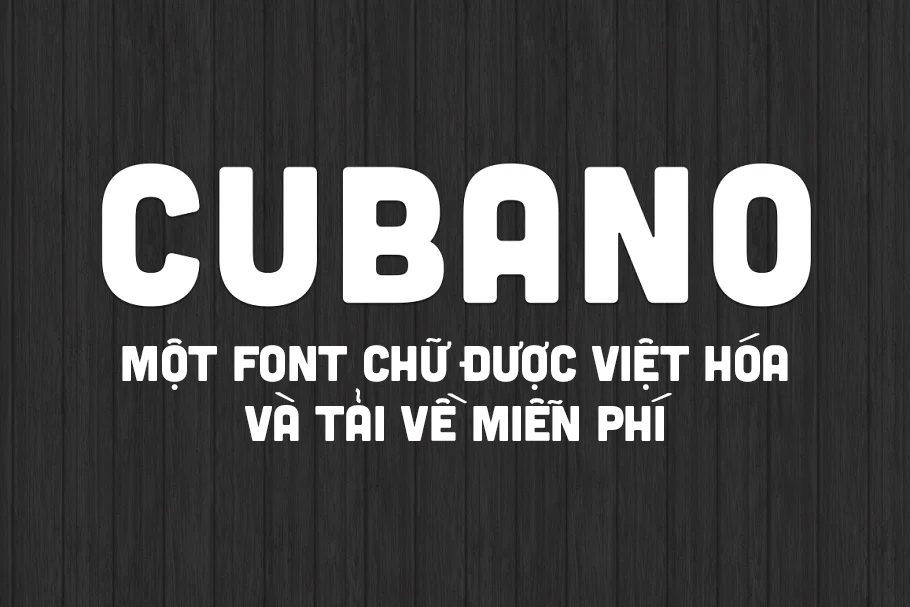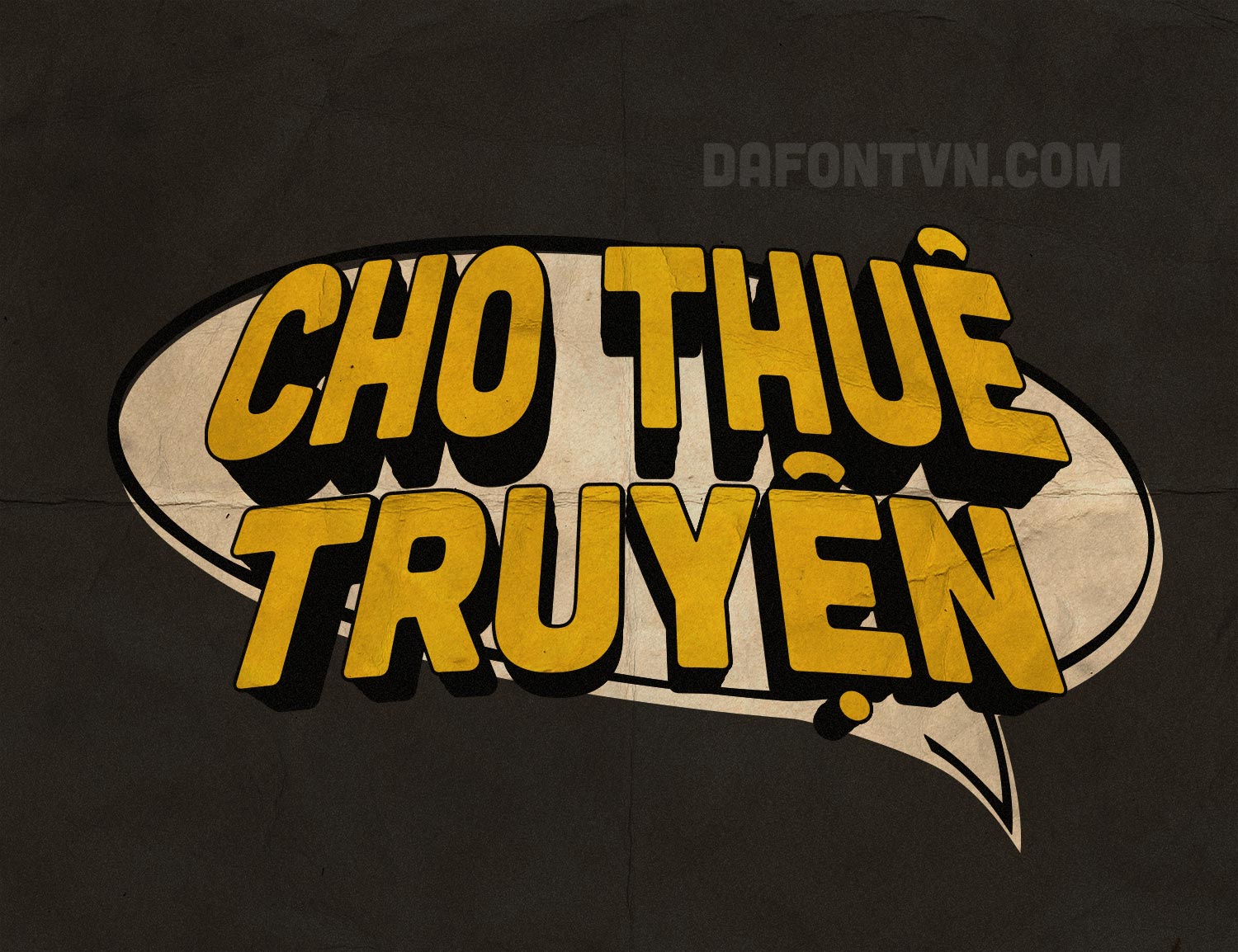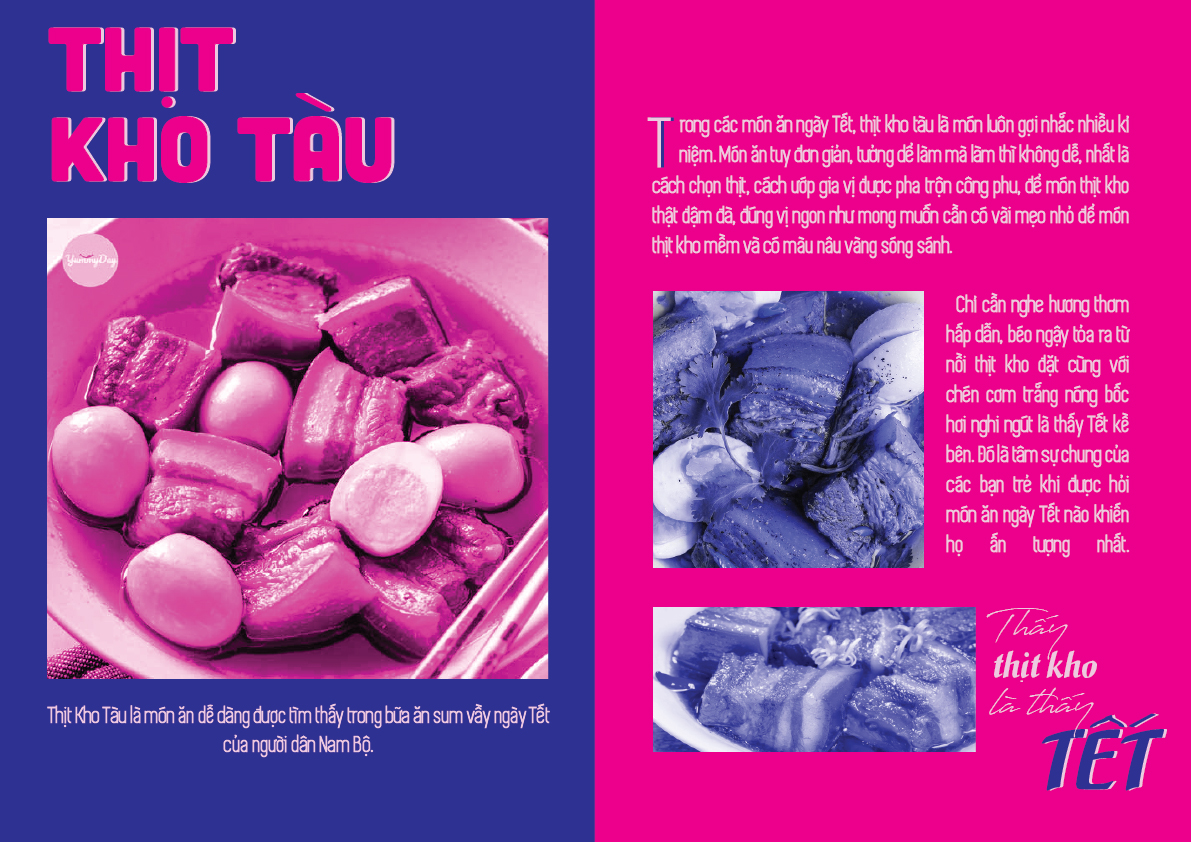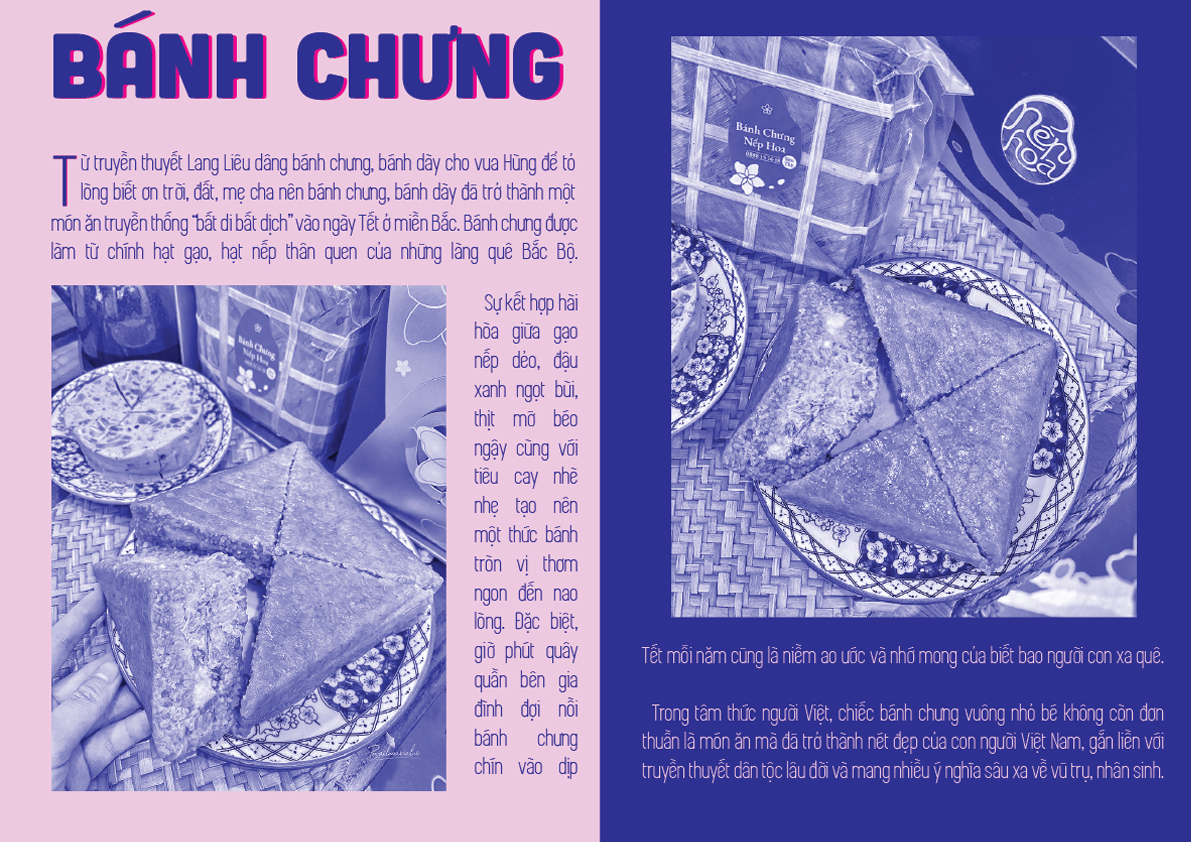
[Display] Font iCielBC Cubano Việt Hóa
iCielBC Cubano Việt Hóa là một trong những font miễn phí nằm trong bộ font Hòn Ngọc Viễn Đông được việt hóa bởi iCiel. Font Cubano được thiết kế với các góc tròn, nét vẽ rộng. Với 167 glyphs, Cubano có sẵn trong tất cả các chữ hoa với chữ số, dấu câu, biểu tượng và hầu hết các dấu trọng âm.